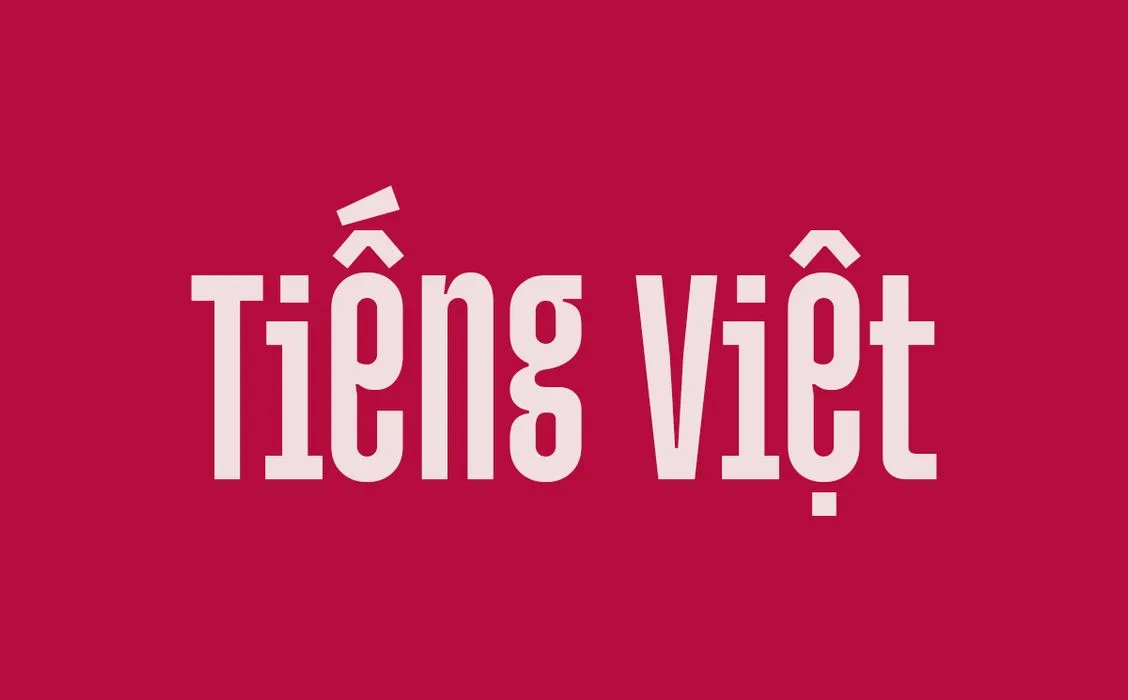
Font chữ VL Monologue Việt hóa với những đường nét góc cạnh, cứng cáp tạo nên một ấn tượng mạnh mẽ, thể hiện sự quyết đoán và chuyên nghiệp. Được thiết kế theo phong cách hiện đại, VL Monologue phù hợp với nhiều loại hình thiết kế như logo, poster, banner, đặc biệt là những ấn phẩm liên quan đến công nghệ, thể thao hay các sản phẩm dành cho nam giới.
Với VL Monologue, bạn có thể tạo ra những thiết kế độc đáo, thu hút sự chú ý và khẳng định phong cách riêng biệt. Font chữ này đã được Việt hóa hoàn toàn, giúp bạn dễ dàng sử dụng trong các dự án thiết kế của mình.